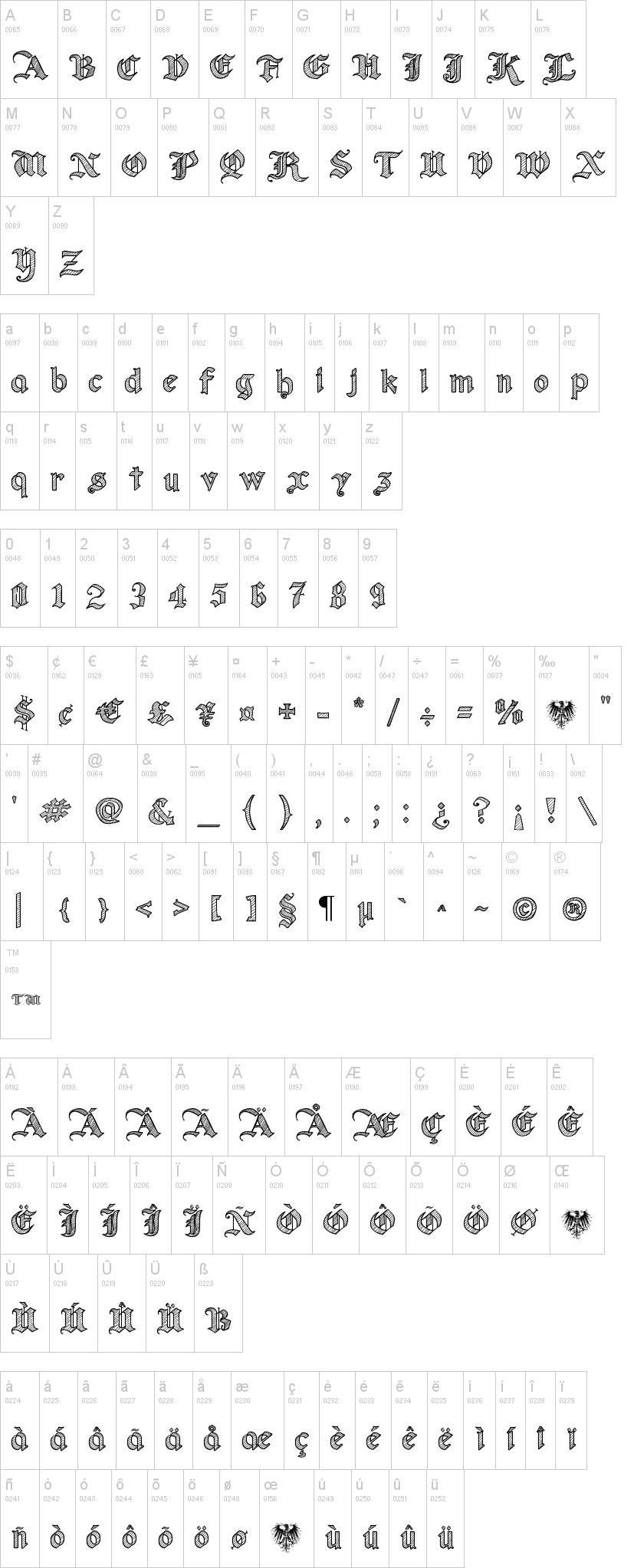
Old Wise Sketch
Old Wise Sketch 是一款免费的手写风格的字体,它拥有独特的草图感和艺术气息。这个字体的每一个字母都是由手绘而成,因此每一个字母都有着独特的特点和风格,这使得 Old Wise Sketch 字体有着别具一格的个性和表现力。这个字体适用于各种场合,如卡片、广告、海报等等,它可以很好地吸引人们的注意力,让人们更容易记住所表达的信息。Old Wise Sketch 字体有两种大小写字母和数字,同时也包括了一些常用的符号和标点符号。
Old Wise Sketch是一款非常不错的手写艺术字体,具有很好的视觉感,适合于文化类的宣传设计、商业类品牌的广告和产品包装设计以及个性化文字排版等较多场景。
Old Wise Sketch字符映射图